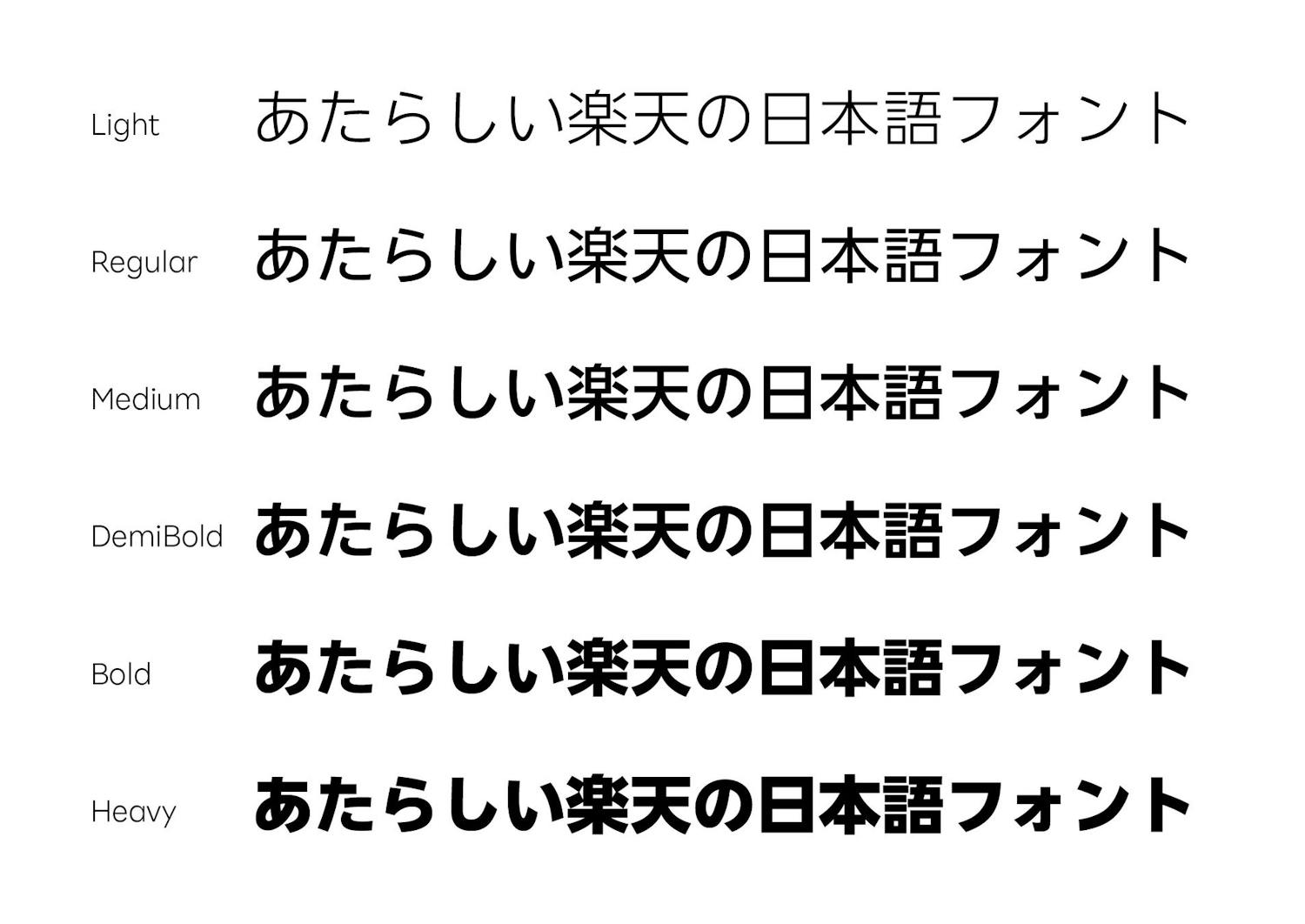
モリサワと楽天が共同で新フォント「Rakuten Sans JP」を開発
楽天グループとフォントメーカーのモリサワが共同で新たな日本語コーポレートフォント「Rakuten Sans JP」を開発しました。この新フォントは既に楽天のコーポレートサイトの一部で使用されているとのことです。
Rakuten Sans JP
楽天はこれまで主に使用してきた欧文コーポレートフォント「Rakuten Font」とモリサワの「UD新ゴNT」から、ブランドの統一感を表現するために新たな日本語フォントの開発に着手しました。
新たに開発された「Rakuten Sans JP」は、欧文フォント「Rakuten Sans」との親和性を持つとともに、楽天のブランドポリシーやTone of Voiceを体現するデザインとされています。また、「楽」と「天」の漢字2文字の形も新たに設計されており、細部までこだわったデザインが施されています。さらに、濁点の重なり方が異なる文字のバリエーションを導入し、使いやすさと可読性の両立を可能にしました。
この新たなフォント「Rakuten Sans JP」は楽天のコーポレートサイトをはじめ、その他のサイトやアプリ、IR資料などで活用される予定とのことです。